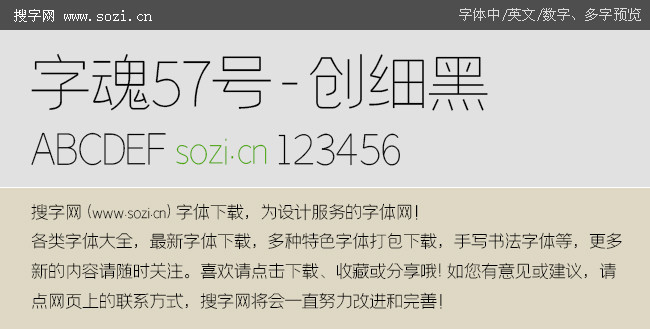
字魂57號-創(chuàng)細黑
搜字網(wǎng)提供一款字魂57號-創(chuàng)細黑中文字體下載,該字體是一款基礎(chǔ)黑體字體,該字體包含6763個中文、字母、 符號和數(shù)字,具有古典、中國風、現(xiàn)代、優(yōu)雅、簡約 的風格,可以滿足您設(shè)計上的各種需求,該字體主要用于屏顯、印章、標志、導視、健康養(yǎng)生、電商、媒體、活動 等場景。